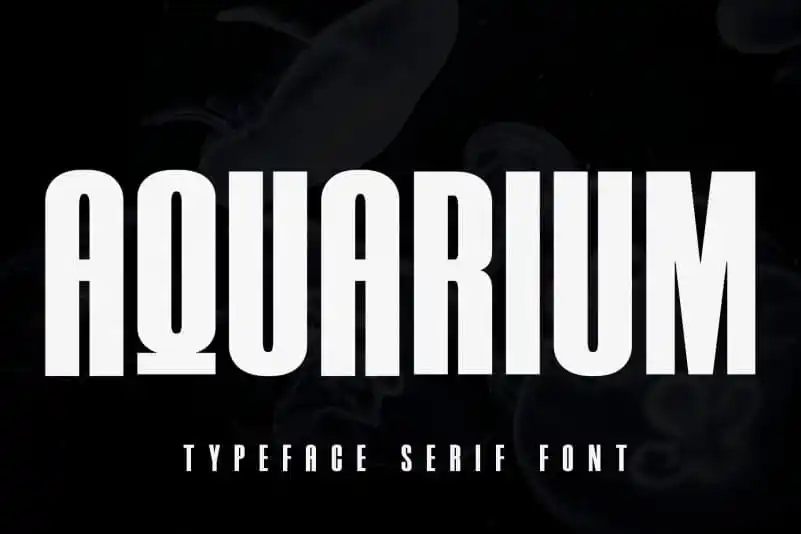
A ‘Aquarium Sans Serif Font’ é uma deliciosa escolha para designers que buscam adicionar um toque inovador a seus projetos digitais e impressos. Com sua tipografia de sans-serif clara e moderna, essa fonte oferece um formato amigável aos olhos, ideal tanto para elementos visuais online quanto para designs offline. Seja você criando uma identidade visual única para uma campanha publicitária ou produzindo etiquetas inovadoras para sua linha de produtos, ‘Aquarium Sans Serif Font’ trará vida e originalidade a qualquer projeto. Suas linhas retas e leves são perfeitas para apresentações de Wall Display criativas, embalagens impecáveis para seus produtos, design personalizado do seu website ou até mesmo criação de watermarks elegantes. E não esqueça que ela se adapta perfeitamente a várias aplicações, desde o design de invitations casuais até os mais profundos designs de estação de impressão. Engane-se com esta fonte e faça dela um componente indispensável do seu arsenal de ferramentas de design.